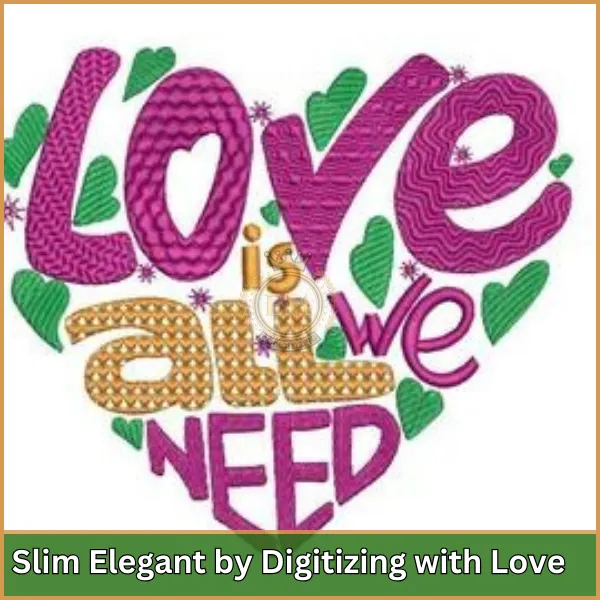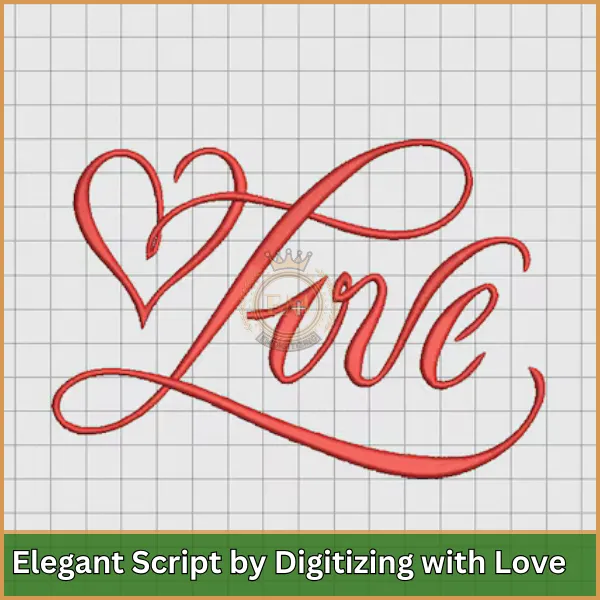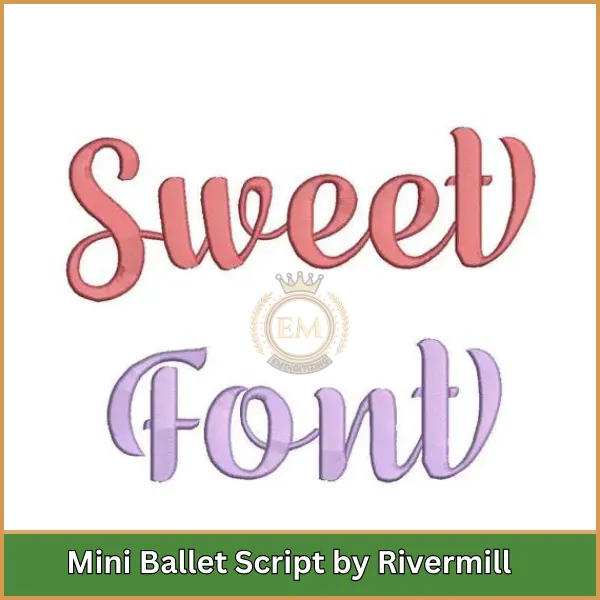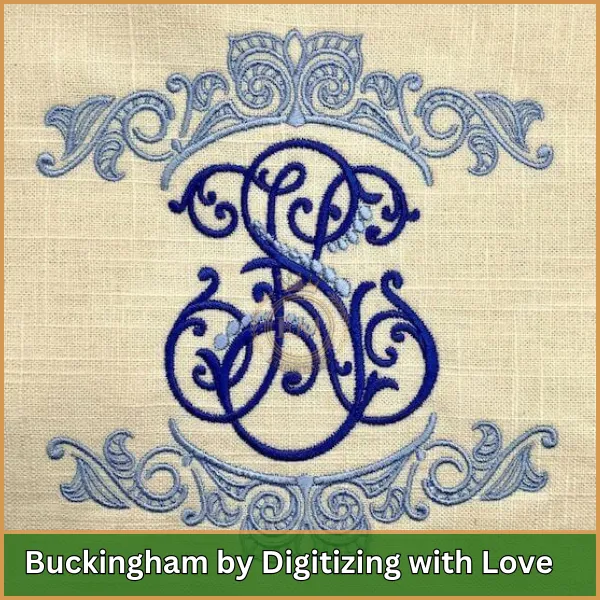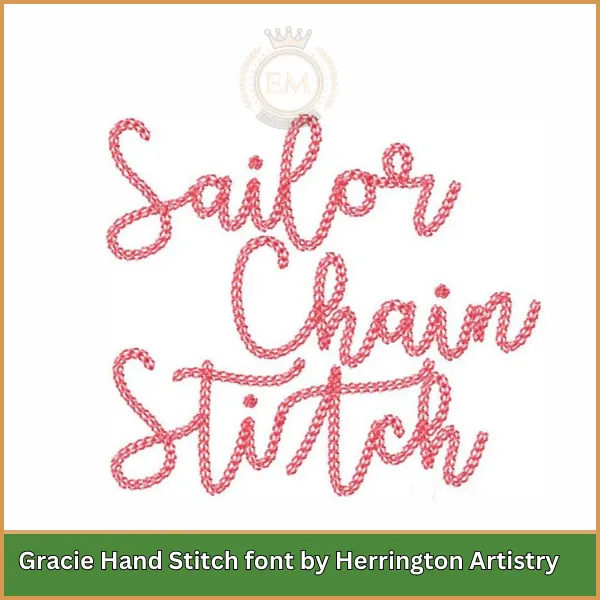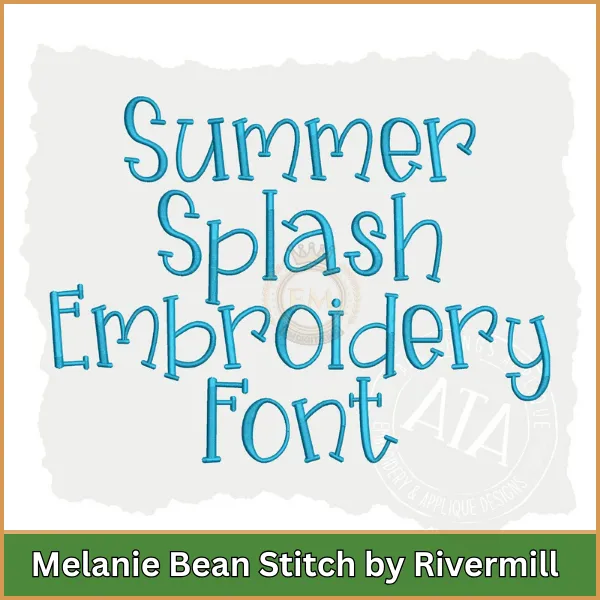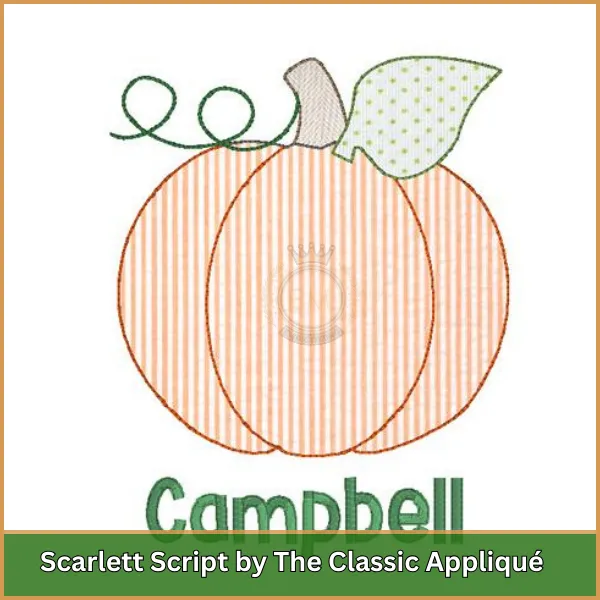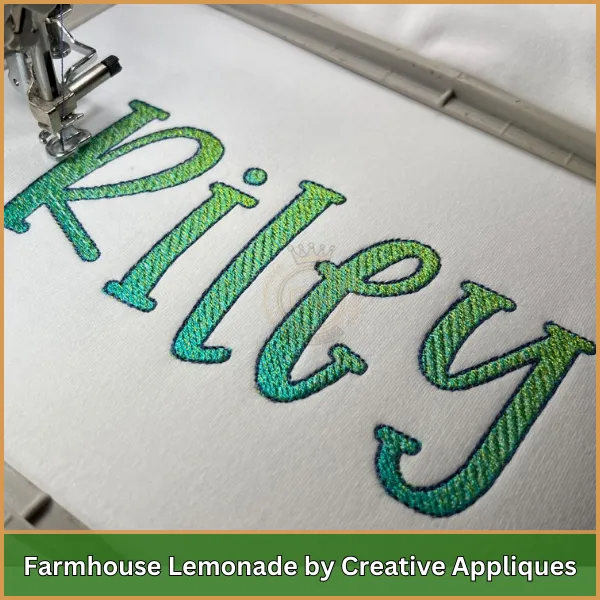
Die besten Skript-Schriftarten für Maschinenstickerei, die Sie ausprobieren sollten
Wenn es um Maschinenstickerei -Skriptschriften geht, Es gibt so viele schöne Optionen! Aber wie wählen Sie den perfekten für Ihre Stickmaschine aus??
Dieser Artikel zeigt Ihnen einige der besten Skript -Schriftarten, die nicht nur hübsch, sondern auch leicht zu treffen sind.
Tauchen wir in die Welt der stilvollen Drehbuch -Stickereien ein, um die zu finden, die genau richtig für Sie ist!
Die besten Skript-Schriftarten für Maschinenstickerei, die Sie ausprobieren sollten
Faktoren, die bei der Auswahl der besten Skriptmaschinenstickereien berücksichtigt werden müssen
Bei der Auswahl der besten Skriptschriften für die Maschinenstickerei, Es müssen mehrere Faktoren berücksichtigt werden, um sowohl die ästhetische Attraktivität als auch die Funktionalität Ihres Designs sicherzustellen. Hier sind die wichtigsten Überlegungen:
• Lesbarkeit: Priorisieren Sie immer die Lesbarkeit. Einige Maschinen -Stickrückschriften können in größeren Größen elegant erscheinen, werden jedoch schwer zu entschlüsseln, wenn sie skaliert werden. Bewerten Sie die Klarheit jedes Charakters an der beabsichtigten Stickgröße.
• Entwurfskompatibilität und Zweck: Passen Sie die Schrift mit dem Thema und Zweck Ihrer Stickerei an. Zum Beispiel, Wählen Sie skurrile Schriftarten für Freizeitprojekte und klassische Skripte für formellere Stücke, Sicherstellen, dass der Schriftstil das Gesamtdesign ergänzt.
Stichdichte und Komplexität
• Stichdichte und Komplexität: Betrachten Sie die Dichte und Komplexität der Skriptschriften. Hochdichte oder komplizierte Schriftarten können zu Problemen wie Thread-Pausen oder ungleichmäßigen Nähten auf empfindlichen Stoffen führen. Wählen Sie Schriftarten, die speziell für Stickereien entwickelt wurden, um eine reibungslose Ausführung zu gewährleisten.
• Stoffeignung: Der Stofftyp kann Ihre Schriftart erheblich beeinflussen. Schwerere Schriftarten eignen sich möglicherweise für dickere Materialien, wohingegen Licht, Für empfindliche Stoffe eignen sich luftige Schriftarten möglicherweise besser. Wählen Sie eine Schriftart, die mit der Textur und dem Gewicht des Stoffes harmoniert.
• Personalisierungs- und Anpassungsoptionen: Entscheiden Sie sich für Schriftarten, die flexible Anpassungsoptionen bieten, z. B. anpassbare Buchstabenabstände und -höhen. Dadurch können Sie die Schriftart genau an Ihre spezifischen Projektanforderungen anpassen, Verleihen Sie Ihrer Arbeit eine persönliche Note.
• Stichqualität: Wählen Sie Schriftarten für Maschinenstickereien aus, die digitalisiert sind, um eine hervorragende Stichqualität zu erzielen. Gut digitalisierte Schriftarten sorgen für reibungslose Nähte, weniger Fadenbrüche, und Klarheit bewahren, Verbesserung der Gesamtqualität der Stickerei.
Durch sorgfältige Berücksichtigung dieser Faktoren, Sie können Schriftarten wählen, die nicht nur den optischen Reiz Ihrer Stickprojekte steigern, sondern auch deren Praktikabilität und Qualität gewährleisten.
Die besten Skript-Schriftarten für Maschinenstickerei
Entdecken Sie die besten Schriftarten für Stickskripte, Jedes bietet seinen einzigartigen Stil und seine Eleganz, um Ihre Stickprojekte wirklich hervorzuheben:
1. Schlank und elegant durch Digitalisieren mit Liebe
2. Elegantes Skript von Digitalizing with Love
3. Mini-Ballett-Skript von Rivermill
4. Buckingham von Digitalizing with Love
5. Gracie Hand Stitch-Schriftart von Herrington Artistry
6. Melanie Bean Stitch von Rivermill
7. Scarlett-Skript von The Classic Appliqué
8. Bauernlimonade von Creative Appliques
9. Schicke Kalligraphie
Jetzt haben Sie einen schnellen Überblick über die Schriftarten, Lassen Sie uns in ihre detaillierten Beschreibungen eintauchen
1. Schlank und elegant durch Digitalisieren mit Liebe
Schlank und elegant durch Digitalisieren mit Liebe
Der Name dieser Schriftart ist passend für ihr schlankes und elegantes Erscheinungsbild, Damit eignet es sich perfekt für formelle Projekte.
Sein zartes Design kann einen Hauch von Raffinesse verleihen Hochzeitseinladungen, personalisierte Geschenke, und andere Artikel, bei denen ein raffiniertes Aussehen gewünscht wird.
2. Elegantes Skript von Digitalizing with Love
Elegantes Skript von Digitalizing with Love
Diese Schriftart hat eine abgerundete Form, verspielterer Charakter als Slim Elegant, Bietet einen weicheren Look für Projekte. It’;Es ist vielseitig, Geeignet sowohl für formelle als auch legere Kleidungsstücke, und fügt Kreationen eine persönliche Note hinzu, ohne übermäßig formell zu sein.
3. Mini-Ballett-Skript von Rivermill
Mini-Ballett-Skript von Rivermill
Das Mini -Ballett -Drehbuch fällt auf seinen komprimierten und kursiven Stil auf, Machen Sie es ideal für lange Texte in begrenzten Räumen.